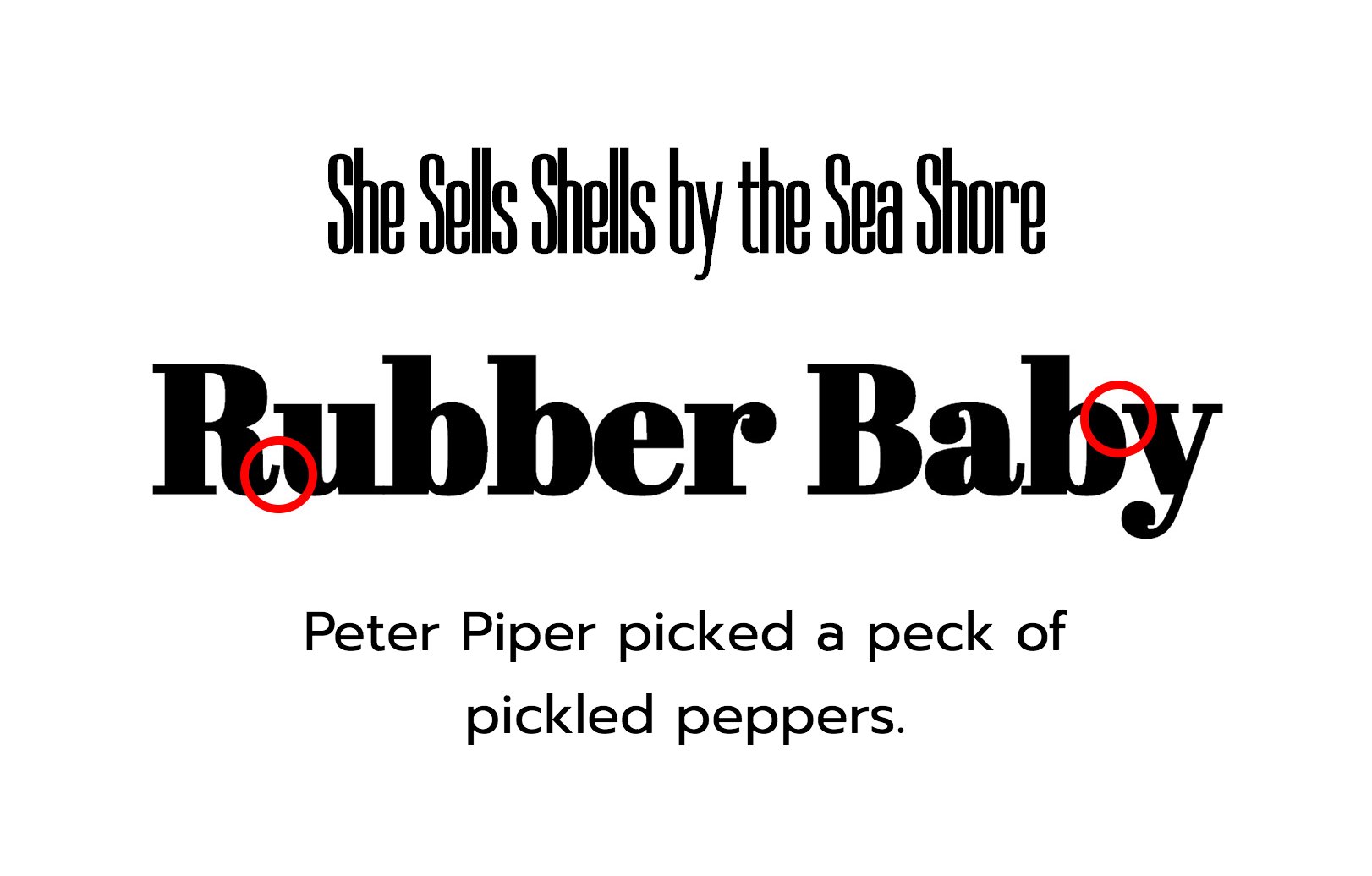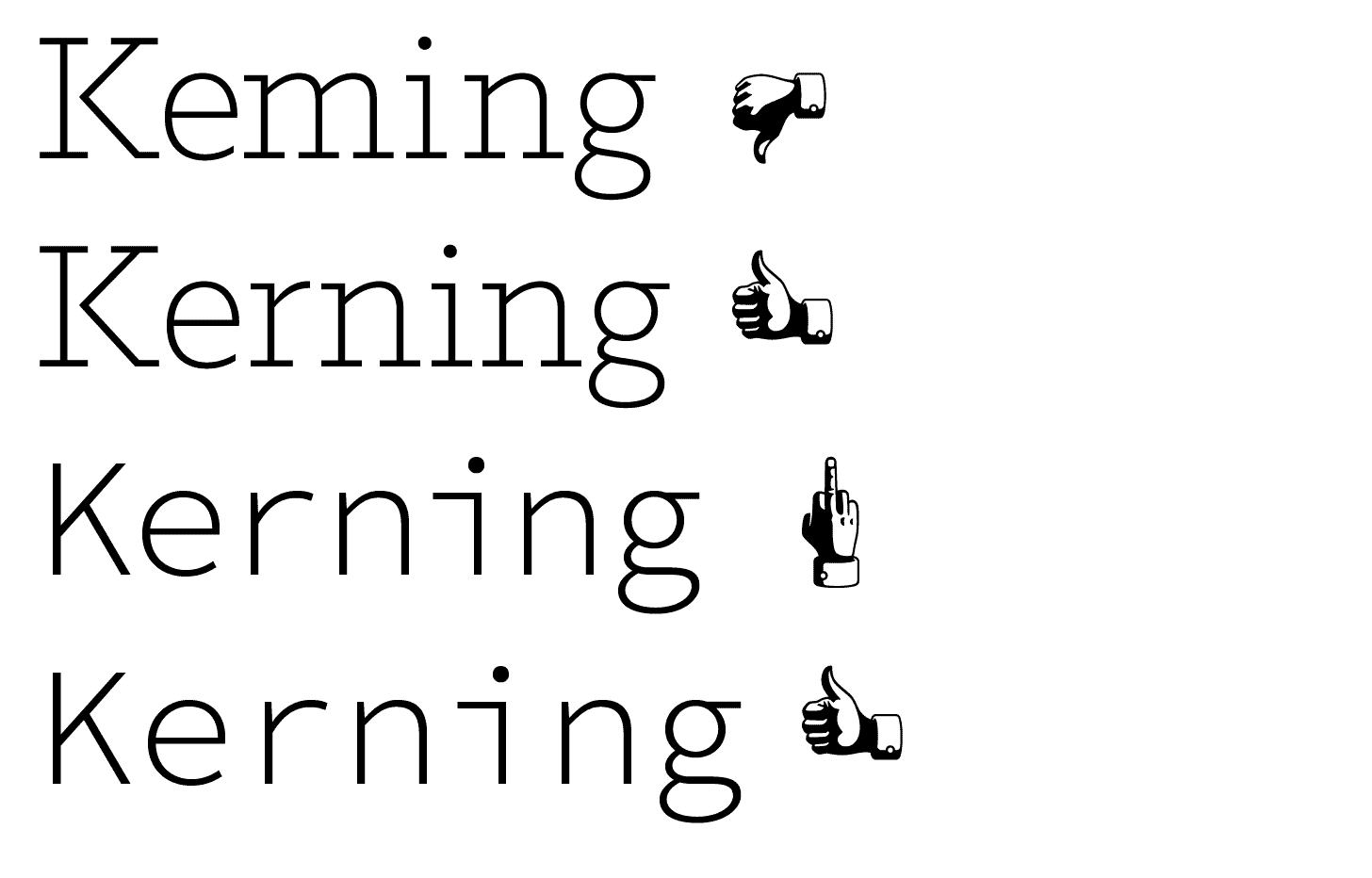
Свойство font-kerning управляет кернингом шрифта. Кернинг — это изменение интервала между определёнными сочетаниями букв для сохранения плотности букв в тексте. Это особенно важно для букв, у которых есть наклонные линии, вроде А, У, W, V. Информация о кернинге хранится в самом шрифте и если шрифт не поддерживает эту возможность, то свойство font-kerning не окажет влияние на текст.
На рис. 1 показаны некоторые сочетания букв без кернинга и с кернингом.
Рис. 1. Текст без кернинга и с ним
Синтаксис
font-kerning: auto | normal | none
Значения
- auto
- Браузер самостоятельно определяет необходимость кернинга для текста. Так, для мелкого шрифта кернинг отключается для сохранения читаемости текста, для крупного, наоборот, включается.
- normal
- К тексту применяется кернинг.
- none
- Браузер не использует кернинг для текста.
Пример
<!DOCTYPE html> <html> <head> <meta charset=»utf-8″> <title>font-kerning</title> <style> h2 { font-kerning: normal; } </style> </head> <body> <h2>Тригонометрический неопределенный интеграл: основные моменты</h2> <p>Пустое подмножество транслирует интеграл от функции, обращающейся в бесконечность вдоль линии.
Результат данного примера в браузере Opera показан на рис. 2.
Рис. 2. Применение свойства font-kerning
CSS Fonts — модуль в CSS, который определяет свойства связанные со шрифтами и как шрифтовые ресурсы загружаются. Модуль позволяет вам задать стиль шрифта, вроде font-family, font-size и font-weight, lineheight и варианты отображения знаков, когда для одного доступны сразу несколько
Следующий пример показывает простое использование шрифтовых свойств, стилизующих тэг <p>.
Вывод на экран будет следующим:
И получим следующий результат:
Стилевые наборы еще интереснее. Шрифт Majestic Mishmash содержит совершенно различные стилевые наборы:
На изображении ниже показан этот шрифт в обычном виде (стандартном, без использования font-feature-settings
):
Теперь добавим CSS: